Typography đóng một vai trò rất quan trọng trong trải nghiệm người dùng, và để typography thực sự hiệu quả thì bạn phải biết đến và sử dụng những font chữ hiện đại và đẹp. Hôm nay RGB sẽ giới thiệu đến các bạn 4 fonts chữ cực hot đang là xu hướng và cách để có được chúng (hầu hết là miễn phí nhé!).
1. Brandon Grotesque
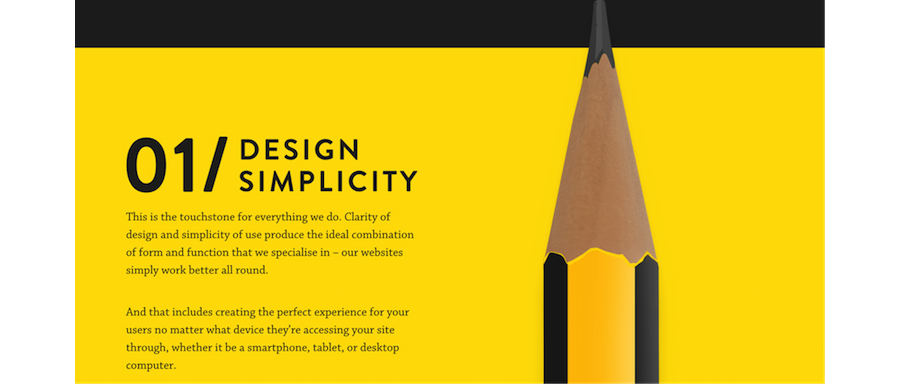
Đây là một font chữ ấm nóng rất đẹp lấy cảm hứng hình học từ phong cách sans-serif được rất nhiều các websites hiện đại ưa chuộng. Nhờ vào độ đậm/nặng (weight) đa dạng, font chữ này sẽ giúp bạn tạo ra độ phân cấp trực quan (visual hierarchy) rất ấn thượng. Ngoài ra nhìn nó cũng rất sạch sẽ, hiện đại và dễ đọc, các bạn có thể kiểm chứng qua trang web này. Bên cạnh đó các bạn cũng có thể xem qua một số ví dụ về cách kết hợp giữ font Brandon Grotesque và serif ở đây.
2. Museo Sans
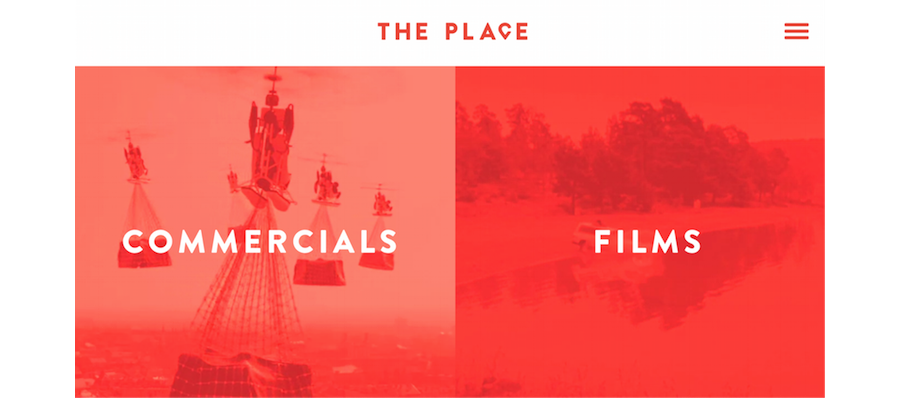
Một font chữ mang phong cách hình học san-serif rất đẹp khác đó chính là Museo Sans. Font này cũng được nhiều websites sử dụng để tạo nên trải nghiệm tuyệt vời cho việc đọc chữ khi được kết hợp với một font serif. Một số ví dụ tiêu biểu như trang web của All Saints Wine và Fast Company. Cũng giống như Brandon Grotesque, bạn có thể tải font này về miễn phí nếu có tài khoản của Adobe CC. (– Bản dịch thực hiện bởi rgb.vn, vui lòng xin phép tác giả khi đăng tải lại)
3. Raleway
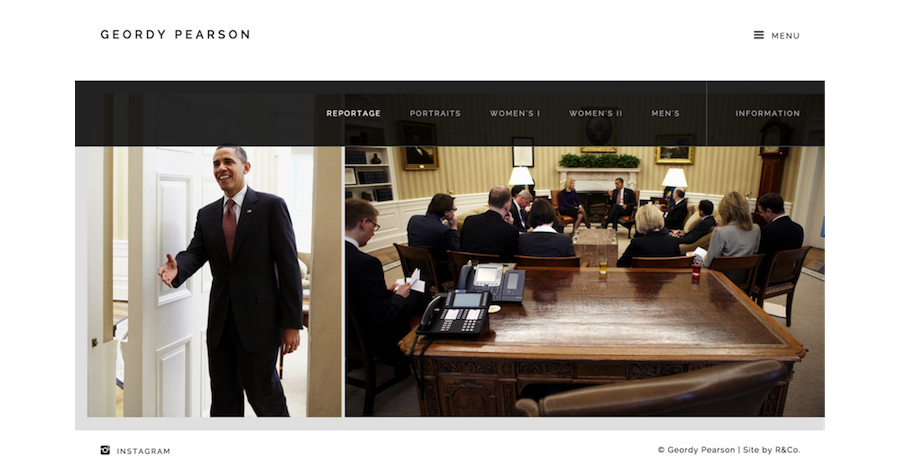
Raleway là một font chữ rất thanh lịch và tinh tế được Google thiết kế. Ban đầu nó chỉ có một độ đậm/nặng thôi nhưng sau đó Google đã tăng lên đến con số 9. Được lấy cảm hứng từ san-serif, chính vì vậy Raleway rất phù hợp khi được kết hợp với font này. Nếu kết hợp đúng cách, Raleway sẽ mang lại cho website của bạn một cá tính rất riêng và ấn tượng. Nhiếp ảnh gia Geordy Pearson cũng sử dụng font này cho trang portfolio của mình. Bạn có thể tải nó miễn phí ở đây.
4. Playfair Display
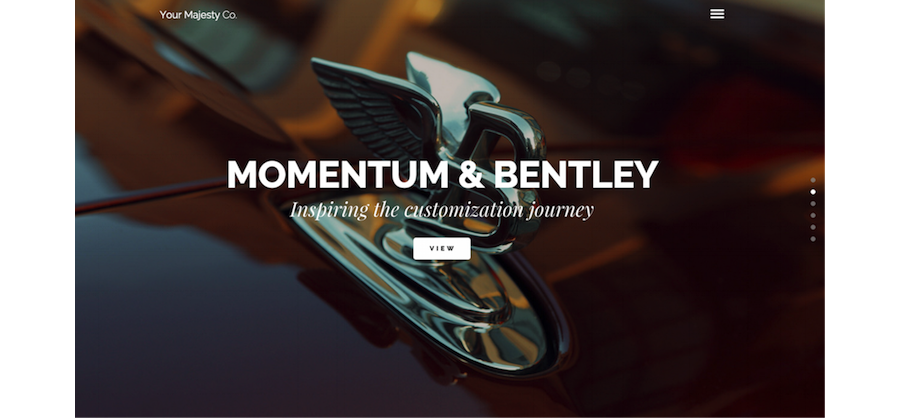
Nghe tên là các bạn cũng có thể đoán ra được, bộ font serif này phù hợp để sử dụng cho tiêu đề và headlines. Mặc dù việc dùng font san-serif cho web đang là mốt hiện nay nhưng khi kết hợp cả serif và san-serif lại với nhau thì kết quả sẽ đẹp và hấp dẫn hơn rất nhiều. Font Playfair này cũng là một font được tạo ra bởi Google, dễ dàng kết hợp với các font san-serif như Raleway, Roboto và nhiều font khác.